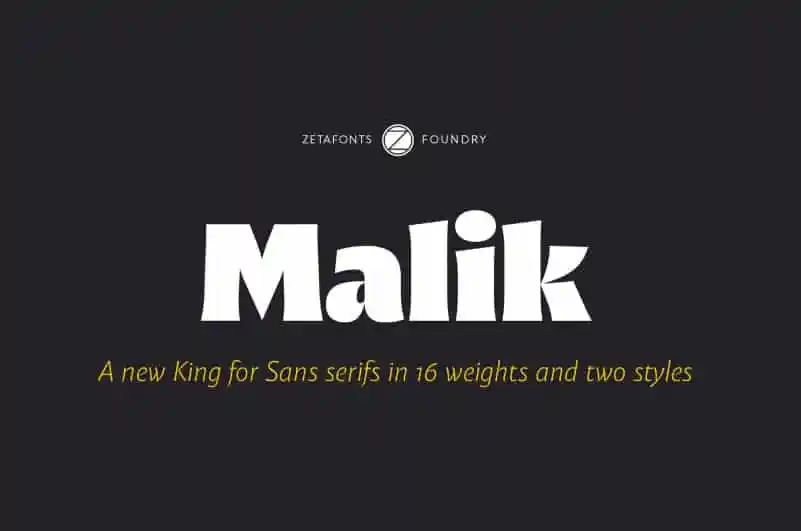
Malik Sans Serif Font Family – Download Grátis
Malik Sans Serif é uma fonte sans serif leve e geometricamente simplificada, projetada para ser fácil de ler e ideal para diversos ambientes digitais. Inspirada no famoso termo árabe de “reis”, Malik combina elementos clássicos dos títulos romanos com a precisão moderna das fontes sans-serif. Andrea Tartarelli, o designer responsável pela criação desta família de tipos, trabalhou para conectar as linhas perfeitas e formais de letras antigas aos traços modernos de legibilidade de hoje. Uma das características que torna Malik única é sua serif flutuada – uma linha pontiaguda que emerge gradualmente da letra, terminando em um ângulo agudo. Este conceito remete às formas singulares do Método Simoncini, uma inovação criada pelo designer tipo italiano Francesco Simoncini para proporcionar uma definição mais clara dos caracteres. Adicionalmente, Malik incorpora a influência de mestres modernos como Frederic Goudy e Ed Benguiat, que destaca-se em detalhes chamigráficos como o B em maiúsculas com contraste invertido, ou o K minúsculo desenhado ao estilo da caligrafia. É uma fonte elegante e sofisticada que traz a modernidade às estilizações clássicas de letras.